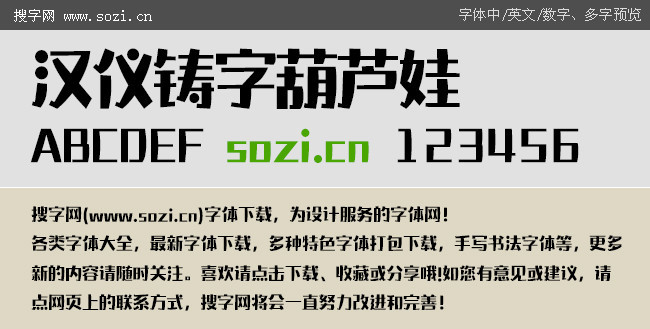
漢儀鑄字葫蘆娃
搜字網(wǎng)給大家提供一款漢儀鑄字葫蘆娃中文字體下載,漢儀鑄字葫蘆娃字體該字體筆觸較為粗實(shí),字形端莊且清晰,適用于畫(huà)冊(cè)設(shè)計(jì)、海報(bào)設(shè)計(jì)、包裝設(shè)計(jì)等場(chǎng)合使用。(本字體為個(gè)人非商用版,如需要商用請(qǐng)聯(lián)系漢儀公司購(gòu)買(mǎi)版權(quán))